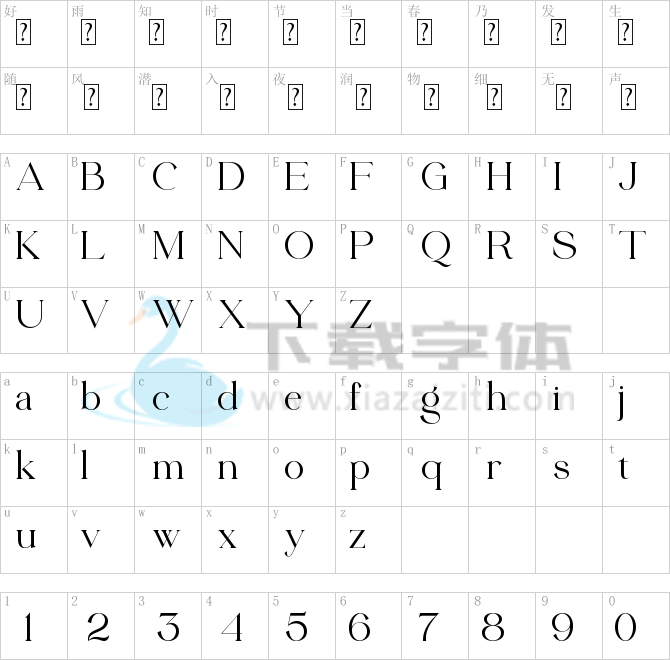
Normal.ttf字体下载,这款字体结构工整、笔画清晰,兼顾美观与易读性,适用于标题、正文、海报、包装、LOGO 等多种场景。字形优雅稳定,风格百搭耐看,适配日常排版与创意设计,让文字呈现更舒适、更具质感。Normal.ttf字体下载一笔一画,皆是细节,以均衡的比例、流畅的线条打造舒适视觉体验,字形端正大气,风格简约现代。无论是商业设计、品牌宣传还是日常排版,都能轻松驾驭,让文字更有格调与力量。Normal.ttf字体下载字体下载。